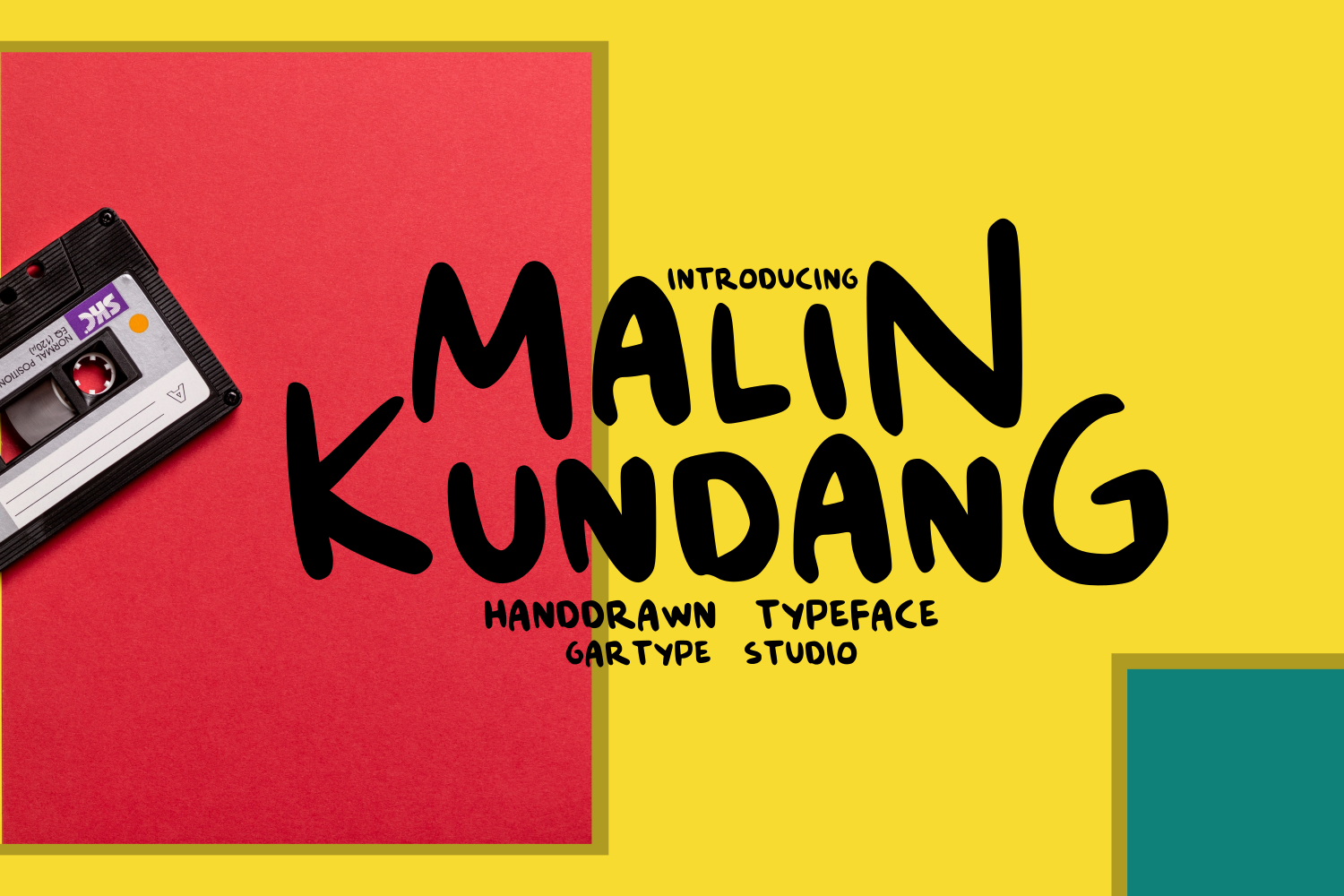
Esteve procurando por uma fonte que atenda a diversos projetos? O Gartype Studio traz para você as Malin Kundang Fonts, perfeitas para criar diversas apostas e interfaces visuais. Essas fontes são ideais para capas de livros, títulos grandiosos, logotipos memoráveis, cartões de atendimento elegantes, frases inspiradoras e até mesmo postagens chamativas. A Malin Kundang oferece uma ampla variedade de alternativas para tornar seus designs ainda mais interessantes e atraentes. Seja você um criador de arte digitais ou designer gráfico, certamente encontrará na Malin Kundang Font o ideal para sua necessidade. Com ela, transforme seu trabalho em algo único e singular que destacará entre as multidões. Estas fontes são perfeitamente adaptáveis a diferentes formatos de design visual, garantindo que cada detalhe seja expresso com precisão e profissionalismo. Seja qual for o projeto que está por vir, certifique-se de incluir estas Malin Kundang Fonts na sua arsenal de ferramentas para ter uma variedade incrível de opções ao seu alcance.